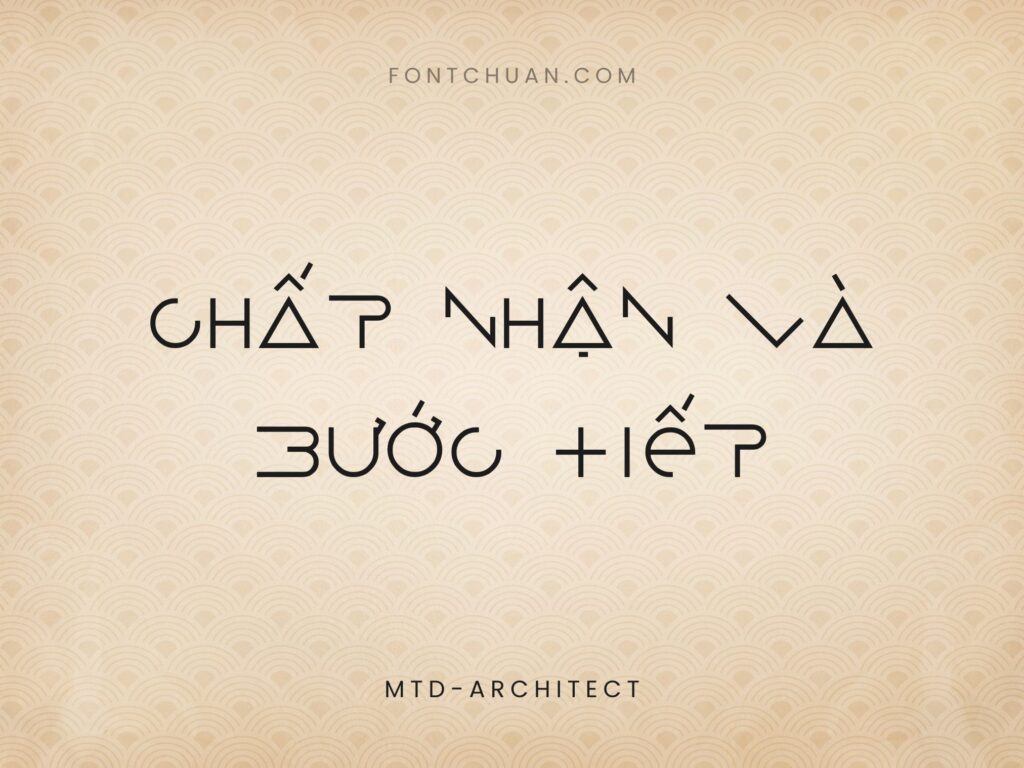
Font Architect là một kiểu chữ mang phong cách bản vẽ kiến trúc cổ điển, được thiết kế để tái hiện lại nét chữ viết tay của các kiến trúc sư trong các bản thiết kế kỹ thuật. Với các đường nét tinh tế và chính xác, font này không chỉ mang lại cảm giác chuyên nghiệp cho các dự án thiết kế kỹ thuật, mà còn rất phù hợp khi sử dụng như một Font logo để tạo sự khác biệt cho thương hiệu.
Phiên bản Architect đã được Việt hóa bởi Mộc Hạ, hỗ trợ đầy đủ tiếng Việt cùng hơn 64 ngôn ngữ khác, mở rộng khả năng ứng dụng trong thiết kế đa ngôn ngữ. Font này đã được thành viên Font Chuẩn sưu tầm và chia sẻ, đáp ứng nhu cầu của cộng đồng thiết kế. Với thiết kế độc đáo, Architect phù hợp cho các ứng dụng như thiết kế logo, tiêu đề, bao bì sản phẩm và các ấn phẩm quảng cáo. Các ngành nghề như quảng cáo, giáo dục, công nghệ và ẩm thực có thể tận dụng font này để tạo ra thiết kế ấn tượng và thu hút.